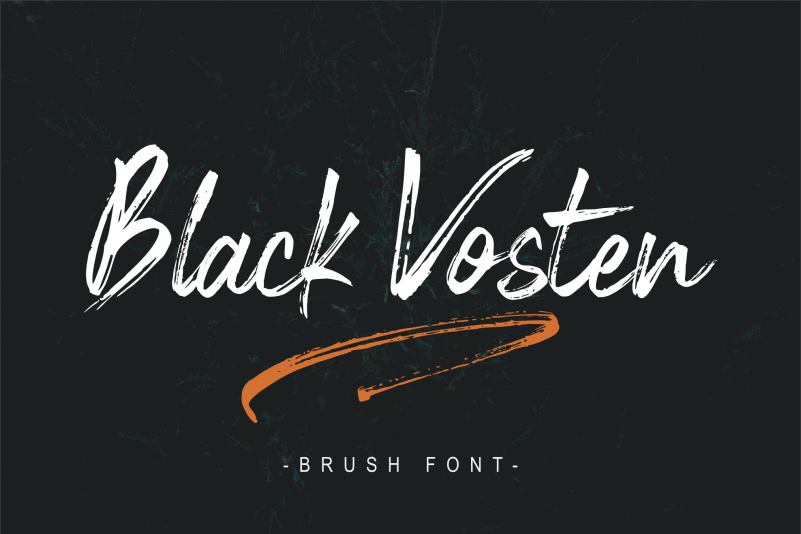
Black Vosten Font – Download Grátis
A Black Vosten Font é uma fonte feita com técnicas de tinta a cepa tradicional, sendo perfeitamente adaptada para o mundo digital e convertida para formato vetorial. Esta criação do designer pandanwangi transmite um sentimento autêntico e relaxado, ideal para aqueles que desejam incorporar uma sensação natural em seus projetos de design. Ela combina os elementos contemporâneos da arte de tinta a cepa com um acabamento elegante, resultando em letras únicas e verdadeiras. Seja você designer ou editor gráfico, esta fonte é o primeiro passo para tornar seu projeto ainda mais interessante e autêntico. Adquira a Black Vosten Font e transforme sua arte digital!